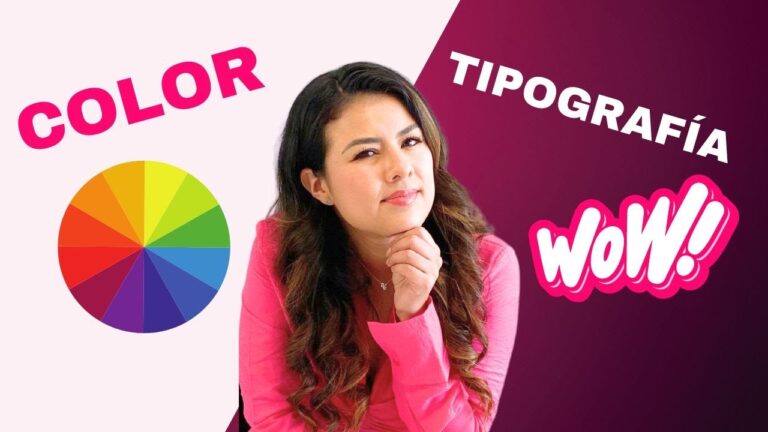
Colores y Tipografía: Claves para una Identidad Visual Impactante
La identidad visual de una marca es fundamental para su reconocimiento y conexión con el público. En este sentido, los colores y la tipografía juegan un papel crítico, ya que son elementos que comunican emociones y valores. Elegir la paleta de colores adecuada y una tipografía coherente no solo define la estética de la marca, sino que también influye en la percepción que los consumidores tienen de ella. En este artículo, investigaremos cómo estos componentes visuales pueden transformar la identidad de una marca y la importancia de su correcta implementación.
¿Cuál es la relevancia de la tipografía en la identidad visual?
La tipografía juega un papel fundamental en la identidad visual, ya que no solo define el estilo y la personalidad de una marca, sino que también influye en la percepción del mensaje que se desea transmitir. Al elegir cuidadosamente las fuentes y su disposición, se mejora la legibilidad y se crea una conexión emocional con el público, haciendo que los textos sean más atractivos y memorables. Una tipografía bien seleccionada puede reforzar la imagen de la marca, destacando su esencia y valores, lo que a su vez contribuye a una comunicación más rendidora y coherente.
¿Cuál es la importancia de los colores en la tipografía?
Los colores en una tipografía son fundamentales para la creación de una imagen de marca sólida y rendidora. A través de la combinación de tonalidades y estilos de letras, se pueden comunicar valores esenciales de la organización, como modernidad, clasicismo o exclusividad. Estas asociaciones visuales no solo capturan la atención del público, sino que también establecen un vínculo emocional, generando confianza y cercanía con la audiencia. Así, la elección adecuada de colores y tipografía se convierte en una herramienta poderosa para diferenciarse en un mercado competitivo.
Creación de Identidad Visual Mediante Tipografía
¿Qué papel juega la tipografía en la identidad visual?
La tipografía juega un papel fundamental en la identidad visual de una marca, ya que no solo comunica información verbal, sino que también evoca emociones y establece el tono de la comunicación. Al elegir tipografías adecuadas, se pueden reforzar los valores de la marca y crear una conexión más profunda con el público objetivo. Cada estilo de letra, desde lo elegante hasta lo moderno, transmite un mensaje diferente, lo que hace crítico su selección.
Además, una buena tipografía contribuye a la legibilidad y claridad del contenido, facilitando que los mensajes sean fácilmente asimilados por el público. La organización de los elementos tipográficos, como el tamaño, el espaciado y el color, también influye en la experiencia del usuario. En resumen, la tipografía es más que una simple elección estética; es un componente esencial que da forma a la percepción y la identidad de una marca en el mundo visual.
Descubre el Poder de los Colores en tu Marca
Los colores son un elemento fundamental en la construcción de la identidad de tu marca, ya que influyen en la percepción y las emociones de los consumidores. Cada tonalidad evoca sensaciones distintas: el azul transmite confianza y seguridad, el rojo despierta pasión y energía, mientras que el verde sugiere frescura y sostenibilidad. Al seleccionar una paleta de colores adecuada, no solo comunicas los valores de tu empresa, sino que también te diferencias en un mercado saturado. Aprovecha el poder de los colores para conectar con tu audiencia y fortalecer la imagen de tu marca, creando una experiencia memorable que resuene en la mente de tus clientes.
Tipografía: El Arte de Comunicar Visualmente
La tipografía es un elemento fundamental en el diseño gráfico y la comunicación visual. A través de la selección de fuentes, tamaños y estilos, los diseñadores pueden transmitir emociones, establecer jerarquías y guiar la atención del espectador. Cada letra cuenta una historia, y su adecuada combinación puede transformar un mensaje ordinario en una experiencia visual cautivadora. Al elegir tipografía, es esencial considerar no solo la legibilidad, sino también la personalidad que se desea proyectar.
La armonía tipográfica se logra al equilibrar diferentes tipos de fuentes y sus características. La alineación, el espaciado y el contraste entre las letras juegan un papel crítico en la creación de una composición visual rendidora. Al combinar tipografías serif y sans-serif, por ejemplo, se puede generar un diálogo entre tradición y modernidad, aportando dinamismo al diseño. Esta interacción no solo embellece el contenido, sino que también refuerza la claridad del mensaje que se desea comunicar.
Finalmente, la tipografía no es solo una cuestión estética; es una herramienta poderosa que puede influir en la percepción del público. Una elección tipográfica adecuada puede mejorar la experiencia del usuario, facilitar la lectura y, en última instancia, fortalecer la identidad de marca. En un mundo saturado de información, dominar el arte de la tipografía se convierte en un factor diferenciador que permite destacar y conectar de manera rendidora con la audiencia.
Estrategias para Crear una Identidad que Resuene